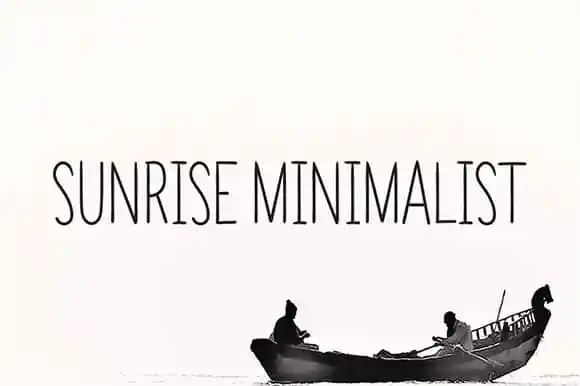
A Sun Rise Minimista Font é uma escolha perfeita para quem busca um estilo moderno que combina elegância com simplicidade. Este tipo de letra serif oferece um toque clássico e sofisticado aos designs, especialmente ideais para aplicativos em grandes tamanhos como ambientes de paredes ou postagens no Instagram, bem como para produtos na embalagem, identidade visual, etiquetas, fotografias e até mesmo marcações. Seja você um designer criando anúncios, um estilista trabalhando em pacotes de produto com design único, uma fotógrafa desejando incorporar a elegância da serif em sua arte digital ou simplesmente alguém querendo dar um toque personalizado à um projeto que exige um quê de autêntica mão-de-obra artística – o Sunrise Minimista é a fonte perfeita. Para quem procura uma fonte moderna e sofisticada, sem perder o charme dos traços serifados tradicionais, esta será sua escolha ideal. É versátil e elegante, adequada para qualquer projeto que busque um toque especial de criatividade e estilo.